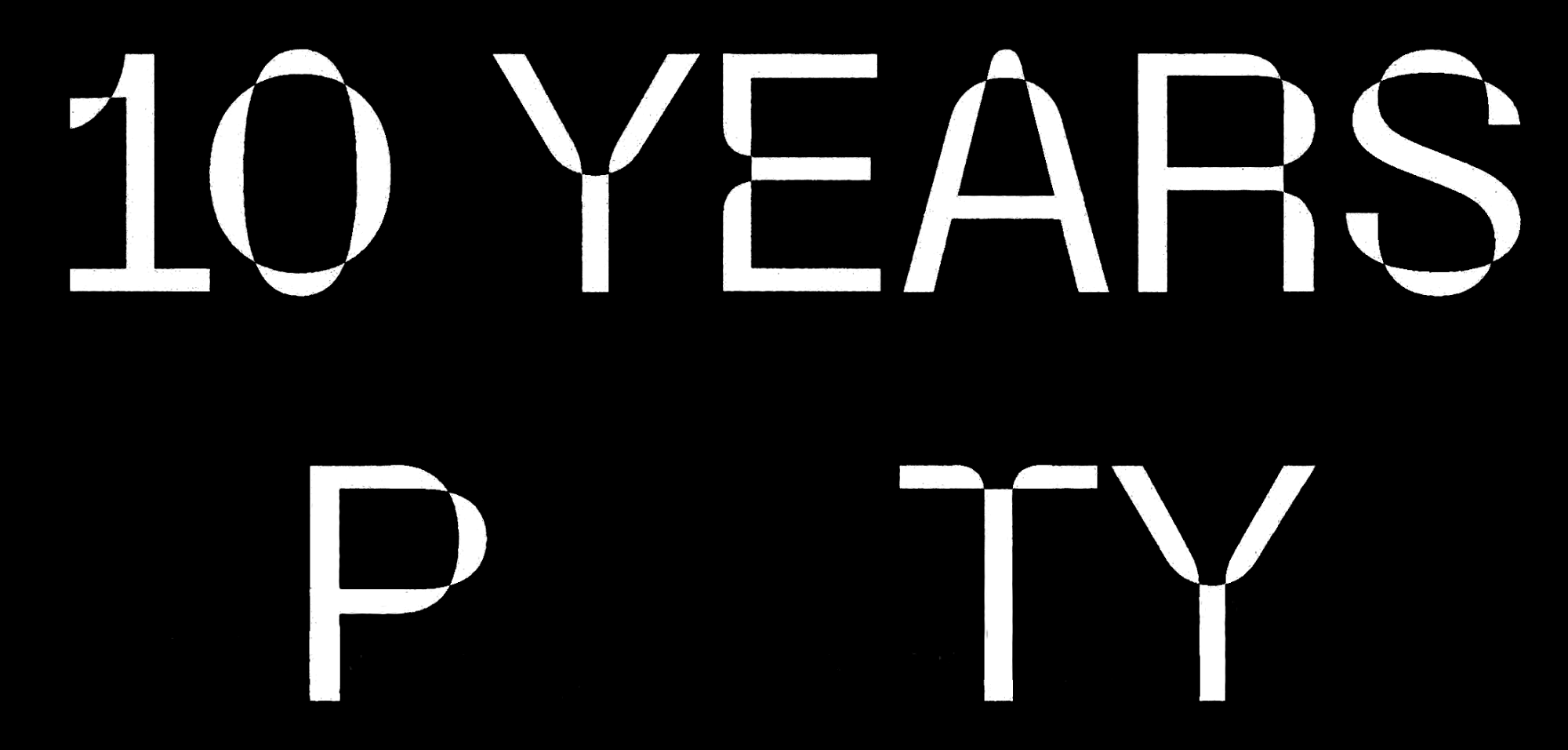
Extrovertierte Schrift entzieht sich der Identifikation. (Café Kapital in der GfzK Leipzig)
Ich bin auf der Suche nach der Schriftart aus dem Bildbeispiel, konnte sie aber weder bei whatfontis noch bei whatthefont identifizieren. Ich habe auch bei googlefonts und myfonts (unter dem Stichwort 'tech') gesucht. Sieht aus, als bräuchte ich einen Schwarm, um sie zu finden. 😄
Könnte möglicherweise eine Freefont oder eine Studentenarbeit sein, obwohl die Kurven sauber gezeichnet sind und gute Entscheidungen getroffen wurden. Wer auch immer diese Schriftart gemacht hat, für mich sieht sie professionell aus.
Leider habe ich auch nicht mehr Informationen und habe gehofft, dass die schon sehr prägnanten Formen für sich sprechen.
Ich würde mich freuen, wenn jemand die Schrift kennt und mir sagt, wie sie heißt. Super wären aber auch, wenn man die Schrift klassifizieren könnte. Experimental Grotesk? Inverted curves? Wonach könnte man googeln?
Ich tippe auf ein Studentenprojekt bzw. eine (noch) nicht veröffentlichte Schrift. Wenn du im Café nachfragst sagt man dir sicher wer die Party-Ankündigung gestaltet hat …
Das ist die Parabole von Dávid Molnár. Microboy lag mit dem Studentenprojekt gar nicht verkehrt: Die Schrift stammt aus der ECAL.